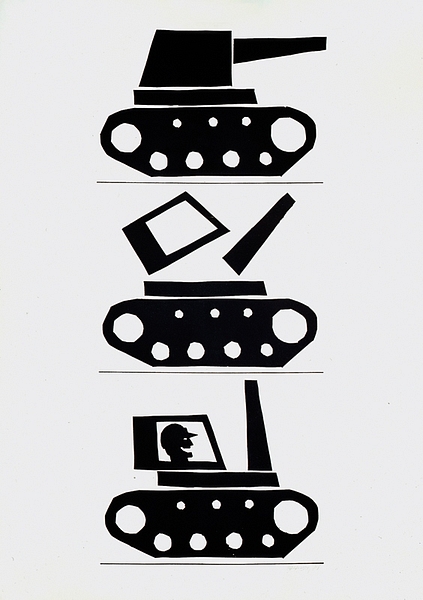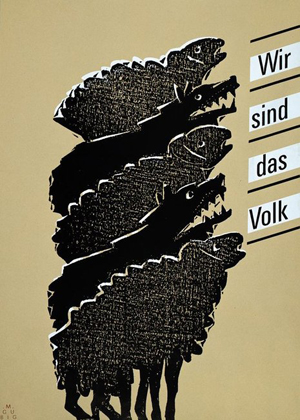
Plakate aus 4 Jahrzehnten DDR
Hat jemand eine andere/bessere Übersicht gefunden als http://www.stiftung-plakat-ost.de/plakate/plak.htm? Dort sehe ich nicht gerade das, was ich für die hohe DDR-Plakatkunst halte.
Ich erinnere mich an eine Ausstellung Mitte der 80er in Havelberg mit Dutzenden mehr oder weniger subtil – aber für gelernte DDR-Bürger™ unübersehbar – regimekritischer Plakate. Von diesem vielleicht wichtigsten Genre der DDR-Plakatgestaltung ist kein einziges Beispiel zu sehen. :evil:
Wieso bzw. in welcher Hinsicht sollten "regimekritische" Plakate in der DDR das "vielleicht wichtigste Genre der DDR-Plakatgestaltung" gewesen sein?
Gibts da jetzt ein Sonderbienchen für (nachträgliche) politische Correctness? Oder sollten ausgerechnet die herausragenden gestalterischen Ideen im Untergrund geblieben sein und offizielle DDR-Plakatkunst war mal wieder nur doof, wie das ja gelegentlich von einigen bildenden Künstlern und Möchtegernliteraten schon in Bezug auf Bildende Kunst und Literatur behauptet wird?
Der DDR-Bürger war geübt, Zwischentöne wahrzunehmen in den offiziellen Verlautbarungen. Das fing schon damit an, wie sich der Funktionär "unsere Menschen" im Bild vorstellte und was Künstler dann aus ihren Aufträgen machten und wie sie, ihr Publikum kennend, Winke gaben, die verstand, wer wollte und konnte. Die verlinkte Übersicht zeigt den virtuosen Umgang mit dieser Bildsprache und grafischen Techniken.
Drei Beispiele:
Rudolf Skribelka zeigt den Stechschritt, und daß den die NVA pflegte, während die Bundeswehr am Wochenende blaumachte, wußten wir aus eigener Erfahrung.
Das Plakat von H.F. Büttner hat man, wenn man wollte, auf sich bezogen.
Der rote Spatz in dem FDJ-Liederplakat von Manfred "Bofi" Bofinger (der nie unter dem Verdacht des Opportunismus stand) streckt stramm die Faust aus, während die anderen Blödsinn machen.
Es war mitunter auch eine Kunst, solche Motive an den Funktionären vorbei zu publizieren.
Dort sehe ich nicht gerade das, was ich für die hohe DDR-Plakatkunst halte.
Wie bitte? Die Plakate von Baltzer, Lubina, Büttner oder Bofinger
(um nur einige zu nennen) gehören zweifellos zu den besten Plakaten,
die jemals in Deutschland produziert wurden. Das erkenne ich
auch als gelernter Wessie neidlos an.
Ich finde ja den Begriff "Genre regimekritischer Plakate" so spaßig. Bisher kannte ich nur "Theaterplakate", "Filmplakate", "Veranstaltungsplakate", "politische Plakate", "Arbeitsschutzplakate" etc. als Plakat-"Genres".
Wenn Plakate in der DDR offiziell gedruckt wurden (und das betraf ja bis auf einige wenige "Untergrundplakate" aus möglicherweise dissidentischer Künstlerszene praktisch alle Plakate, die in der Öffentlichkeit zu sehen waren), dann waren die von den geschätzten Kollegen oben erwähnten Anspielungen auch von den jeweils "Abnahme"-Verantwortlichen genehmigt. Nun sollte man sich aber nicht einbilden, dass diese "Zensoren" alle nur Idioten waren und alle Anspielungen nicht mitbekommen haben, sondern man könnte eben eingestehen, dass die DDR-Kulturpolitik halt doch nicht so ideologisch-stur gleichgeschaltet war wie man das heute im Nachhinein gerne darstellt. Das betrifft im Übrigen ja auch die Literatur, bildende Kunst, Theater, Filme usw. Die DDR war zumindest in den 70er und 80er Jahren nicht das, was wir uns heutzutage unter Nordkorea vorstellen. Und auch als "Nicht-Opportunist" war man nicht gleich "Regimekritiker" - es gab da glücklicherweise eine sehr breite und vielfältige Schicht dazwischen und das sollte man auch differenzierter als in Gut-Böse betrachten. Vermutlich würde kein "Regime" die gegen das eigene System gerichtete Propaganda selber machen ...
Es gab sicher offizielle "(Ost-)Regimekritische (Propaganda-)Plakate": im Westen, zumindest in der Adenauerzeit. Die waren aber - soweit ich sie kenne - nicht gerade die Höhepunkte deutscher Plakatgestaltung. Ob die aber ein eigenes "Genre" bilden?
Ich kann die Darstellung von Gutenberger nur unterstreichen. Der Zensur-Apparat war ein kompliziertes Gebilde, und auch manch ein Leiter eines einer politischen Organisation angeschlossenen Verlages (beispielsweise hing der Kinderbuchverlag Berlin direkt an der FDJ und verstieß unentwegt gegen die Wunschbilder der spröden sozialistischen Pädagogik von Margot Honecker), also offiziell ein Staatsdiener, setzte trickreich Bücher durch, die nicht hundertprozentig der vorgegebenen Linie entsprachen. Wir waren durch die engen Familienbeziehungen nach Westdeutschland nie so abgeschottet wie Nordkorea, die Vorstellungen von Freiheit waren nie weg. Die Pflege des kulturellen Erbes war nicht nur ein ziviles Fähnchen der sozialistischen Ideologie, sondern auch eine starke Festung der Bürgerlichkeit, wovon die Buchkunst zeugt, aber auch jene Plakate, in denen es um klassisches Kulturgut geht. Wie wenig schematisch das Gesamtgebilde war, erlebte ich an der eigenen Biografie: Ich wurde einmal, als ich Anfang zwanzig war, für sieben Monate von insgesamt vierzehn Spitzeln überwacht und "bearbeitet". Einer dieser Inoffiziellen Mitarbeiter unternahm den Versuch, die Aufmerksamkeit auf mich zu reduzieren, indem er mich als uninteressant darstellte. Ein anderer, ein NVA-Oberst, also eigentlich ein "Hundertprozentiger", wurde von der Stasi nicht mehr als Informat in Anspruch genommen, weil er nicht eifrig genug meine Delinquenz verfolgte. Ein weiterer Oberst hetzte bei der Stasi gegen einen anderen, der meine Aufmüpfigkeit nicht hart genug verfolgt hätte. - Diese Diktatur ist auch deshalb ohne erhebliche Gewalt untergegangen, weil sie aufgeweicht war und in weiten Teilen ihre Überzeugung verloren hatte. Mit einem Schema nach Ideologen hie und Dissidenten da ist die DDR nicht zu verstehen. Das gilt auf unterschiedliche Weise für jede Diktatur, nehme ich an.
Die Ausstellung ist phantastisch. In einem leerstehenden Haus die komplette zweite Etage um den Hof herum, zwei Stunden kann man ruhig mitbringen. So schnell nicht wieder zu sehen. DDR-Geschichte, großartige Gebrauchsgrafik, viele bekannte Namen, aus heutiger Sicht freilich komische Konsumwerbung, Hygiene, Gesundheit, lustiger Arbeitsschutz, Musik, Malerei, und von den plumpen Agit-Prop-Sachen fast nichts zu sehen. Eine große Ausstellung wird es im Frühjahr 2013 in Essen geben. Und es gibt einen Katalog mit 300 Plakaten, allen dieser Ausstellung für 20 Euro. Nochmals vielen Dank für den Hinweis!